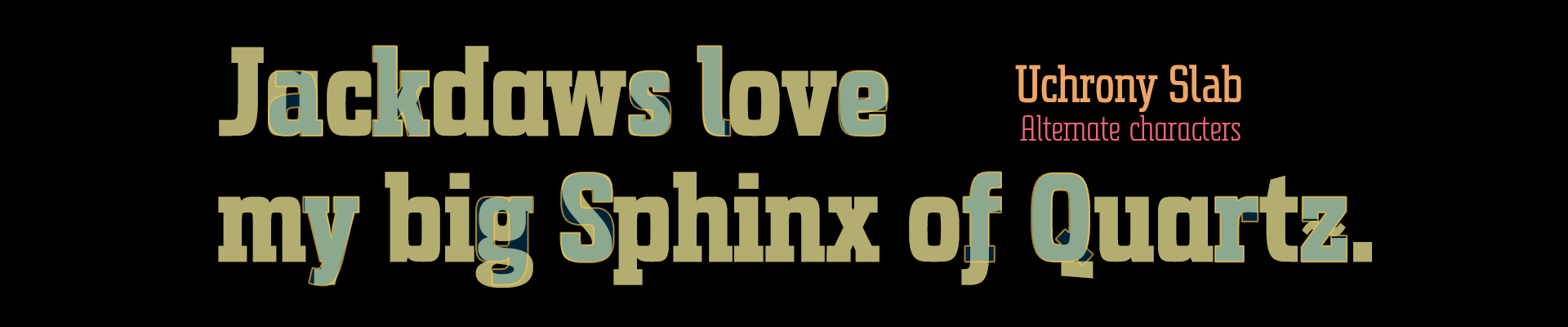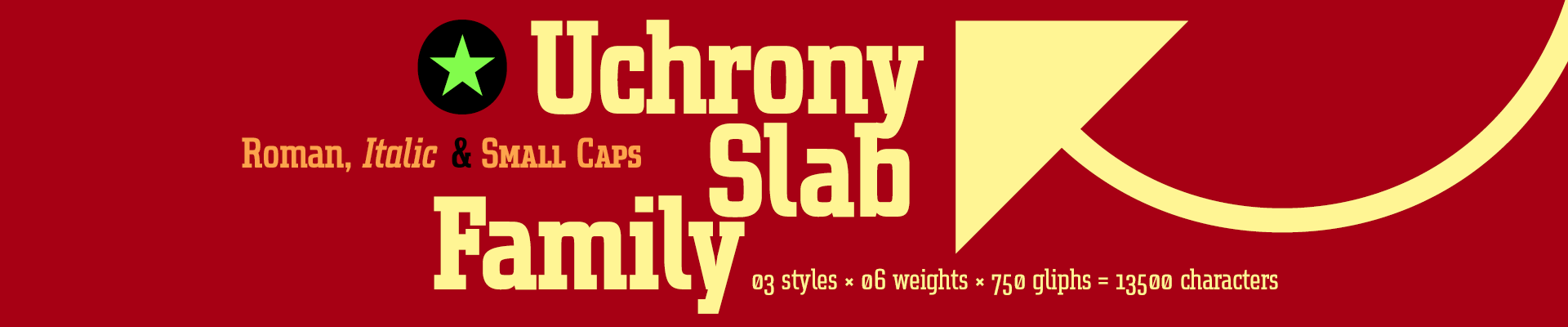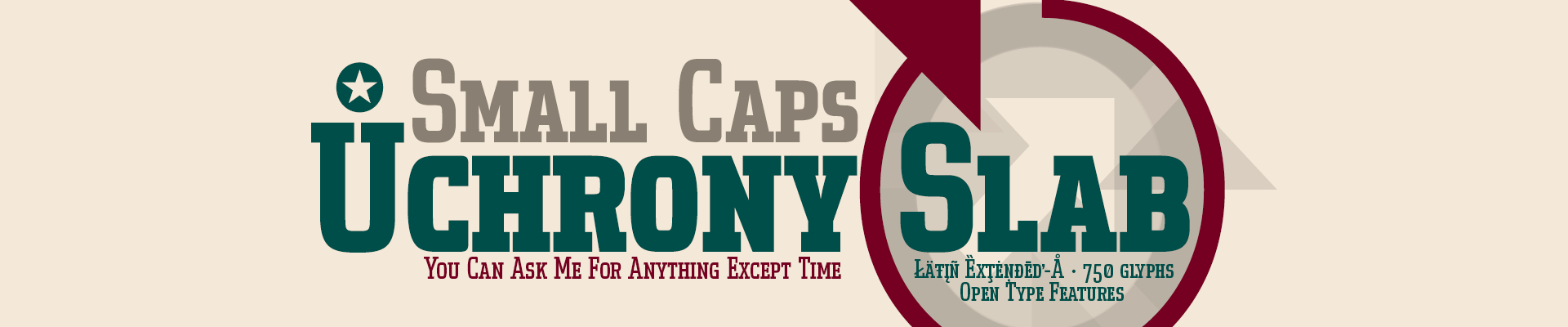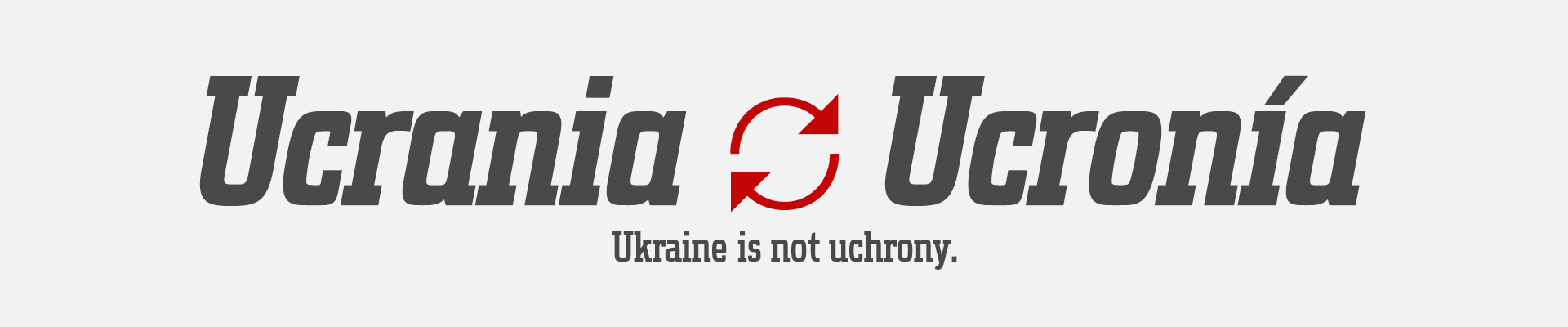
A partir del dibujado de la letra «o» minúscula, he conseguido las proporciones y curvas básicas, que me han permitido dibujar el resto de la tipografía en un ejercicio de construcción minimalista, con esta técnica aporto coherencia morfológica y máxima legibilidad en textos de párrafo y títulos, gracias también, a la cuidada definición de la anchura de cada carácter, en relación con otros, después, la configuración de las métricas y la exhaustiva definición del Kerning, hasta conseguir una familia tipográfica multi propósito, original y totalmente funcional. Todas las versiones incluyen letras alternativas, varios juegos de números y funciones avanzadas OpenType.
Estilo: Slab Serif, Condensed, Small Caps, Roman & Italics, Arrows
Proporción: Extra Light, Light, Regular, Medium, Bold & Extra Bold
Glyphs: 750
Alternates: 87
Latin-Extended: Latín Básico, Europa Occidental, Central & Oriental.
Autor: deFharo
Funciones OpenType: Additional languages, All Alternates, Alternate Annotation Forms, Bitcoin, Capital Spacing, Contextual Alternates, Denominators, Discretionary Ligatures, Extended Fractions, Historical Forms, Inferiors, Kerning, Localized Forms, Numerators, Oldstyle Figures, Ordinals, Scientific Inferiors, Slashed Zero, Standard Ligatures, Stylistic Set, Subscript, Superior letters, Superiors, Superscript, Titling alternates.
A partir del dibujado de la letra «o» minúscula, he conseguido las proporciones y curvas básicas, que me han permitido dibujar el resto de la tipografía en un ejercicio de construcción minimalista, con esta técnica aporto coherencia morfológica y máxima legibilidad en textos de párrafo y títulos, gracias también, a la cuidada definición de la anchura de cada carácter, en relación con otros, después, la configuración de las métricas y la exhaustiva definición del Kerning, hasta conseguir una familia tipográfica multi propósito, original y totalmente funcional. Todas las versiones incluyen letras alternativas, varios juegos de números y funciones avanzadas OpenType.
El uso en diseño gráfico, editorial o publicidad garantiza originalidad y diferencia. Unas fuentes muy versátiles para carteles publicitarios, vídeo juegos, títulos de cine, logotipos, publicaciones, etc. Incluyen el símbolo del Bitcoin y otras Cripto Monedas.
Las fuentes Uchrony Slab Family dispone en su versión comercial de un juego de 750 glifos (Latin Extended-A), todas las versiones con soporte para cualquier idioma europeo o centro europeo. Uchrony Slab también incluye funciones OpenType (Compatibles con InDesign, QuarkXpress, Photoshop e Illustrator.